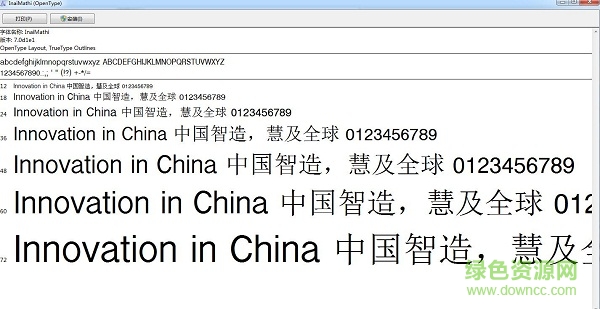
inaimathi字體是一款黑白均勻的無(wú)襯線字體,這款字體字面簡(jiǎn)潔無(wú)裝飾,結(jié)構(gòu)嚴(yán)謹(jǐn),空隙均勻,讀起來(lái)非常舒服,視覺(jué)體驗(yàn)好,可用于電子讀物、網(wǎng)頁(yè)設(shè)計(jì)等領(lǐng)域,歡迎大家免費(fèi)下載!